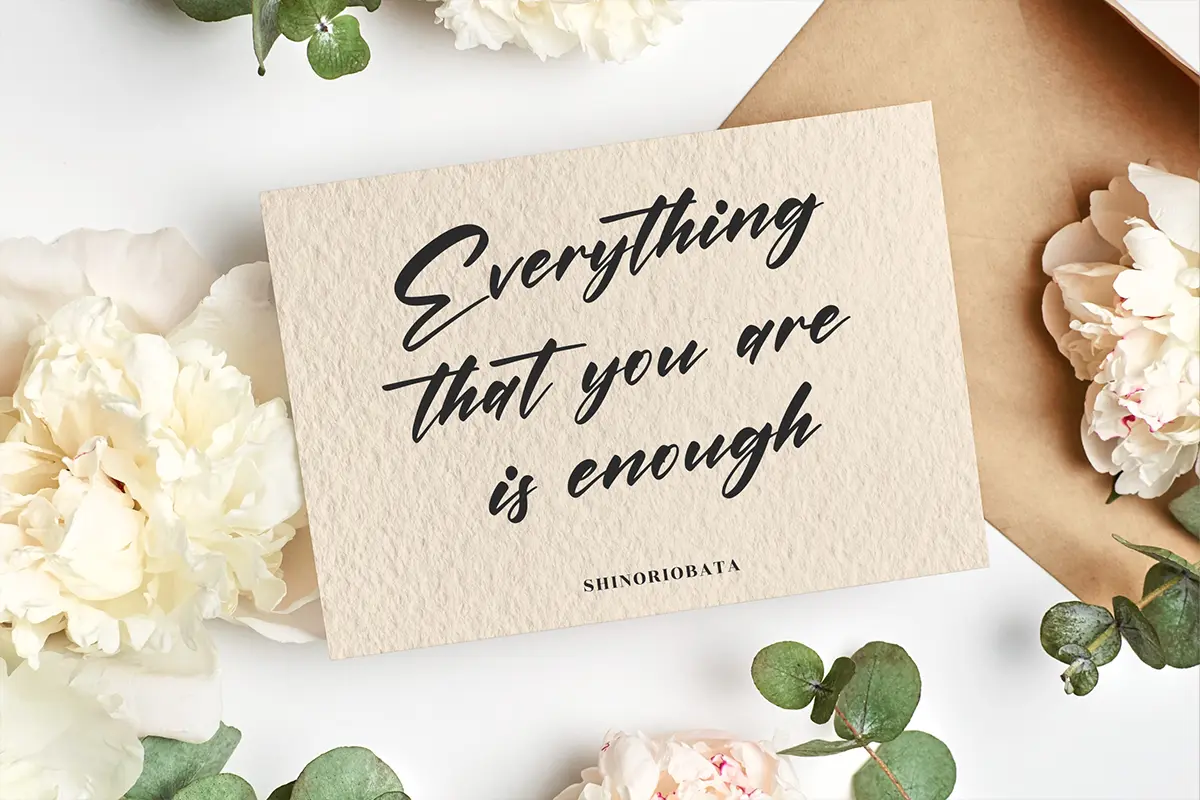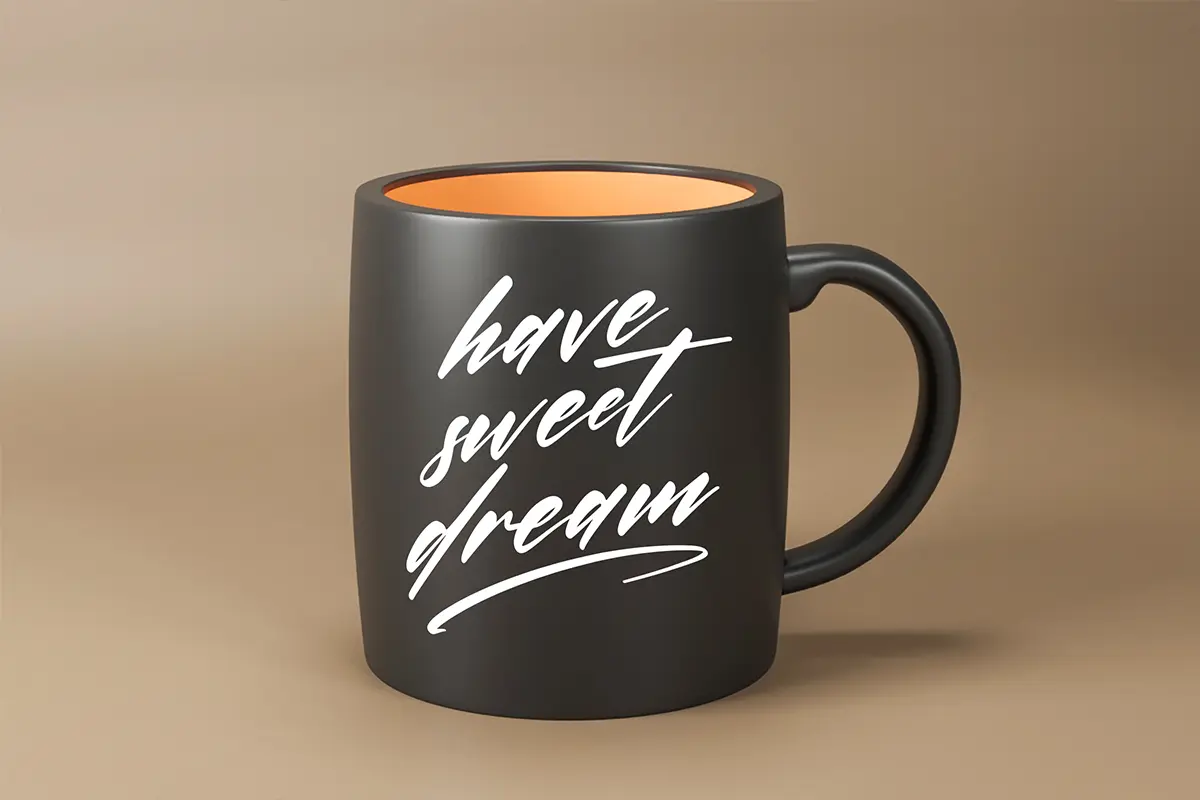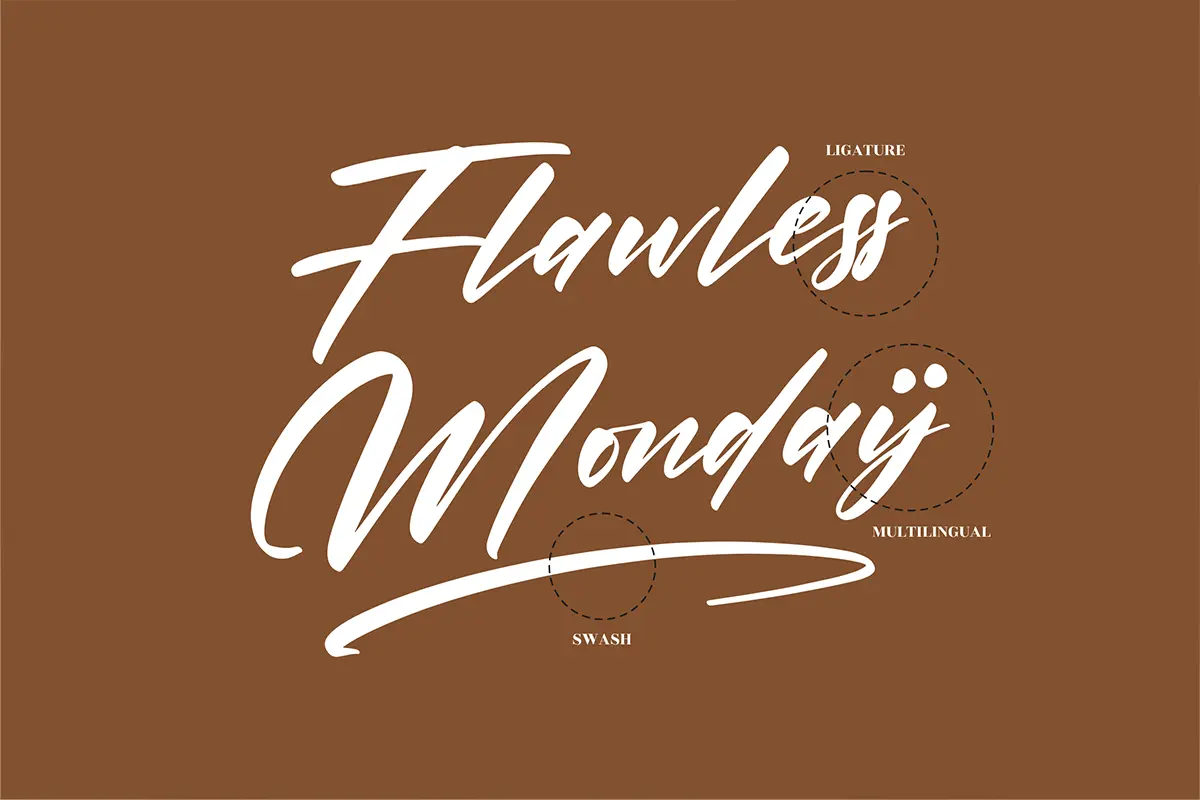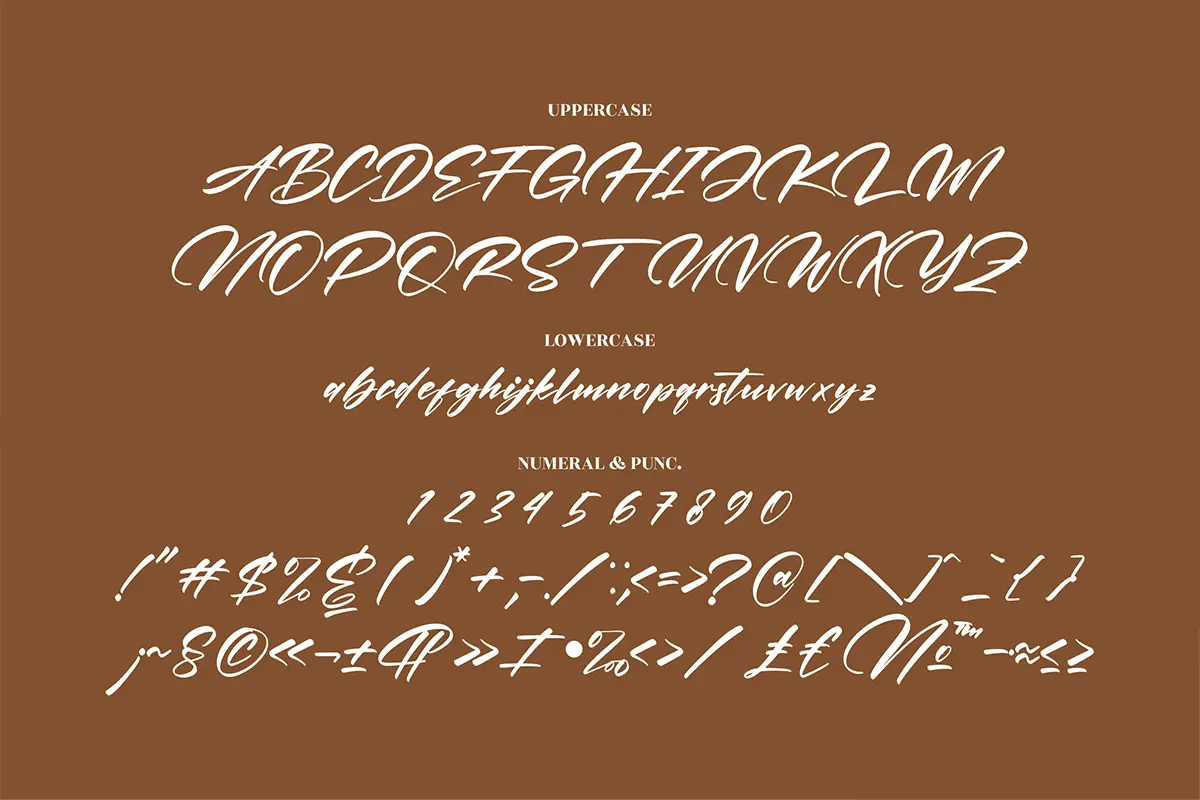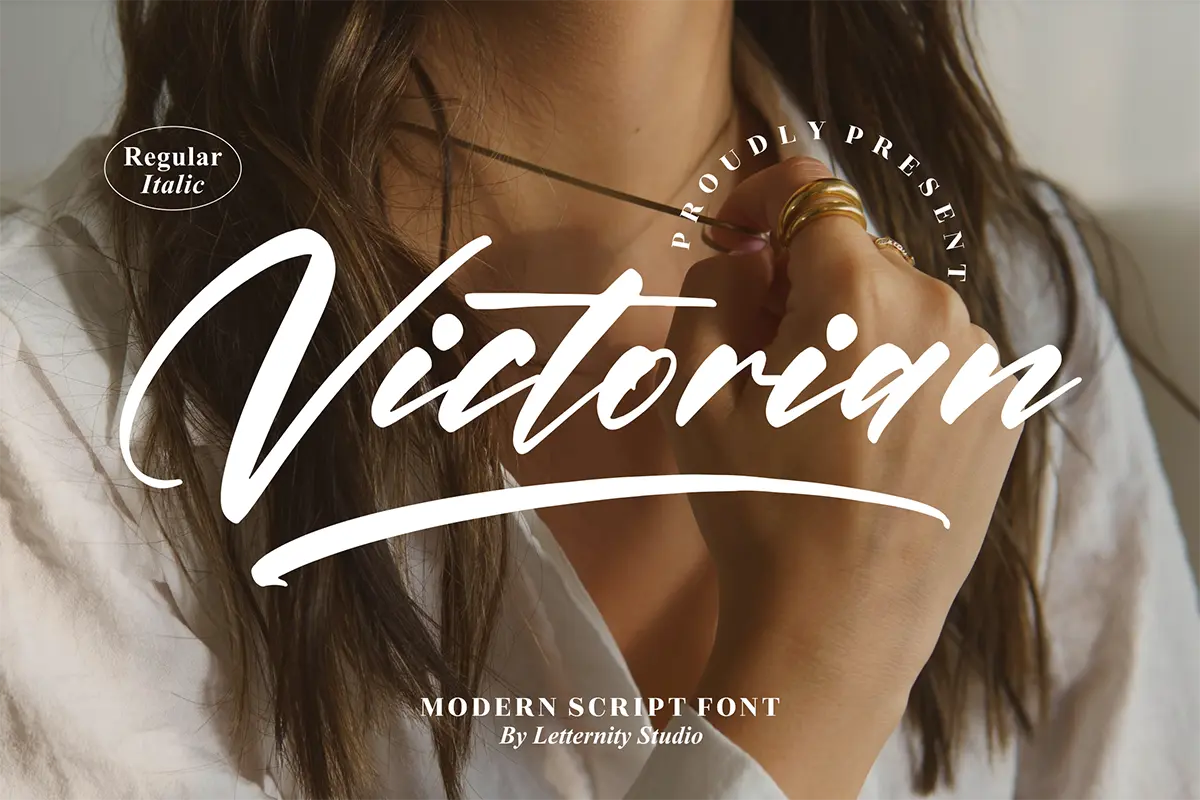
فونت اسکریپت ظریف و الگانت
فونت Victorian یک فونت اسکریپت با حروف باریک و طراحی ظریف و الگانت است که جلوهای لوکس و درخشان به پروژههای شما میبخشد. این فونت برای طراحیهایی که نیاز به حس زیبایی، ظرافت و کلاسیک بودن دارند انتخابی عالی است و میتواند آثار شما را متمایز کند.
ویژگی مهم این فونت، PUA Encoded بودن آن است؛ به این معنا که میتوانید بهراحتی به تمامی گلیفها و لیگچرها دسترسی داشته باشید و طراحیهای شخصیسازیشده و خاص خلق کنید.
⭐ ویژگیهای محصول
- سبک: اسکریپت باریک و ظریف
- حس و حال: لوکس، الگانت و کلاسیک
- PUA Encoded: دسترسی آسان به گلیفها و لیگچرها
- مناسب برای پروژههای دعوتنامه، کارتهای تشکر، لوگوهای لوکس، بستهبندی و تبلیغات
🎯 موارد استفاده
- طراحی دعوتنامههای عروسی و مراسم رسمی
- ساخت کارتهای تشکر و تبریک شیک
- استفاده در لوگوهای برندهای لوکس و کلاسیک
- افزودن حس ظرافت و درخشش لوکس به پروژههای گرافیکی